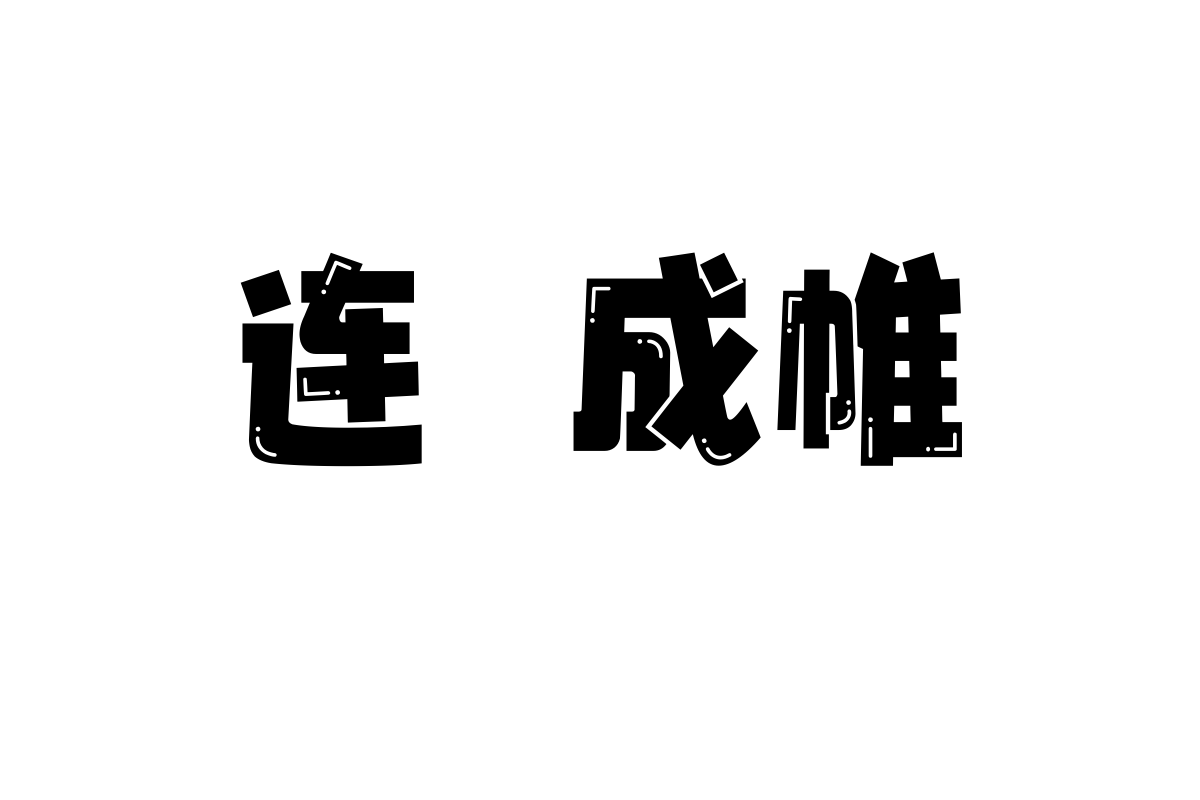
上首雪糕体是一款独特的字体,它结合了现代和古典的元素,创造出一种独特的视觉效果。这种字体的特点是它的笔画粗细不一,给人一种强烈的视觉冲击。
上首雪糕体的字体特点如下:
1. 笔画粗细不一:上首雪糕体的每个笔画都有不同的粗细,这使得它在视觉上产生了一种强烈的对比效果。
2. 线条流畅:虽然笔画粗细不一,但是整体的线条却十分流畅,没有出现断线或者不连贯的情况。
3. 结构复杂:上首雪糕体的字形结构非常复杂,每一个笔画都有其特定的形状和位置,这使得它在视觉上产生了一种立体的效果。
4. 风格独特:上首雪糕体是一种非常独特和新颖的字体,它融合了现代和古典的元素,创造出了一种全新的视觉效果。
总的来说,上首雪糕体是一款非常有创意和个性的字体,它的独特之处就在于它的笔画粗细不一、线条流畅、结构复杂以及风格独特。